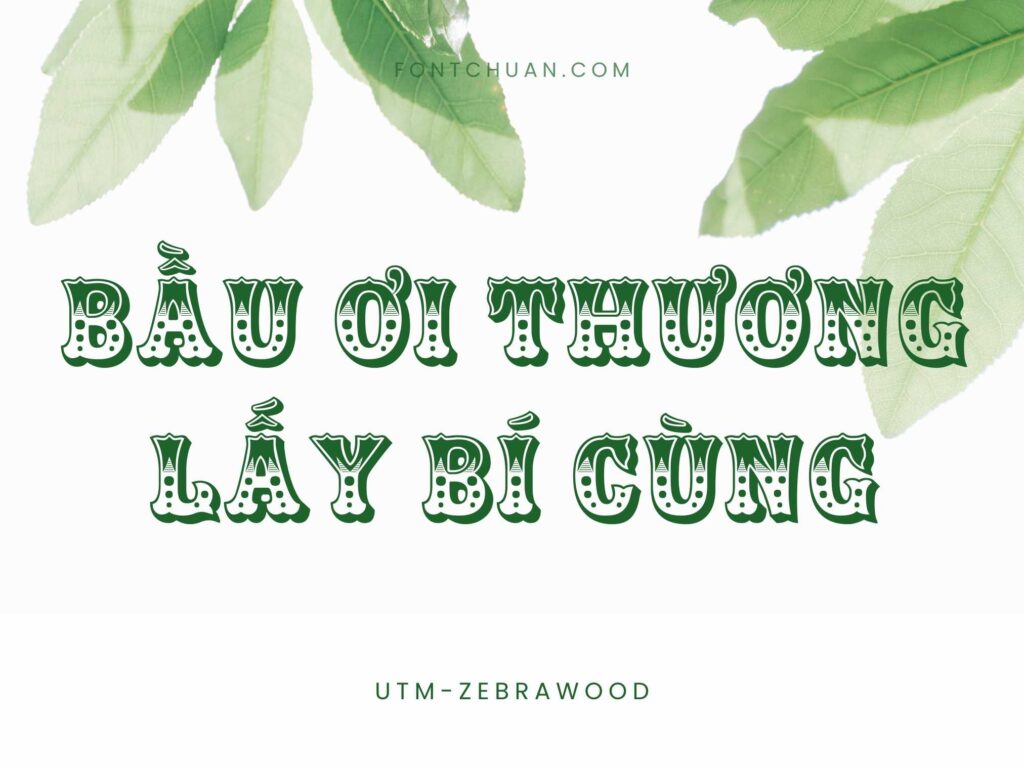
Zebrawood là một font chữ trang trí mang phong cách cổ điển, được lấy cảm hứng từ các kiểu chữ gỗ nổi bật của thế kỷ 19. Font này được phát triển với thiết kế serif đặc trưng, giúp tạo ra hiệu ứng thị giác mạnh mẽ, thường thấy trong các biển hiệu quảng cáo, poster sự kiện và các sản phẩm thiết kế vintage. Với phong cách retro đặc trưng, Zebrawood phù hợp cho những dự án cần sự khác biệt và thu hút.
Font này đã được Việt hóa bởi Thiên Minh, giúp hỗ trợ đầy đủ các dấu và ký tự tiếng Việt, mang lại trải nghiệm sử dụng trọn vẹn. Ngoài tiếng Việt, font còn hỗ trợ hơn 100 ngôn ngữ khác, mở rộng khả năng ứng dụng trong nhiều thiết kế quốc tế. Thành viên của Font Chuẩn đã sưu tầm và giới thiệu font này đến cộng đồng thiết kế để giúp họ có thêm lựa chọn cho các dự án sáng tạo. Zebrawood có đường nét dày dặn, chân serif tách đôi đặc trưng, tạo nên sự vững chắc và cuốn hút trong từng ký tự. Font này đặc biệt phù hợp với các thiết kế poster, logo, biển hiệu hoặc các ấn phẩm mang phong cách vintage.